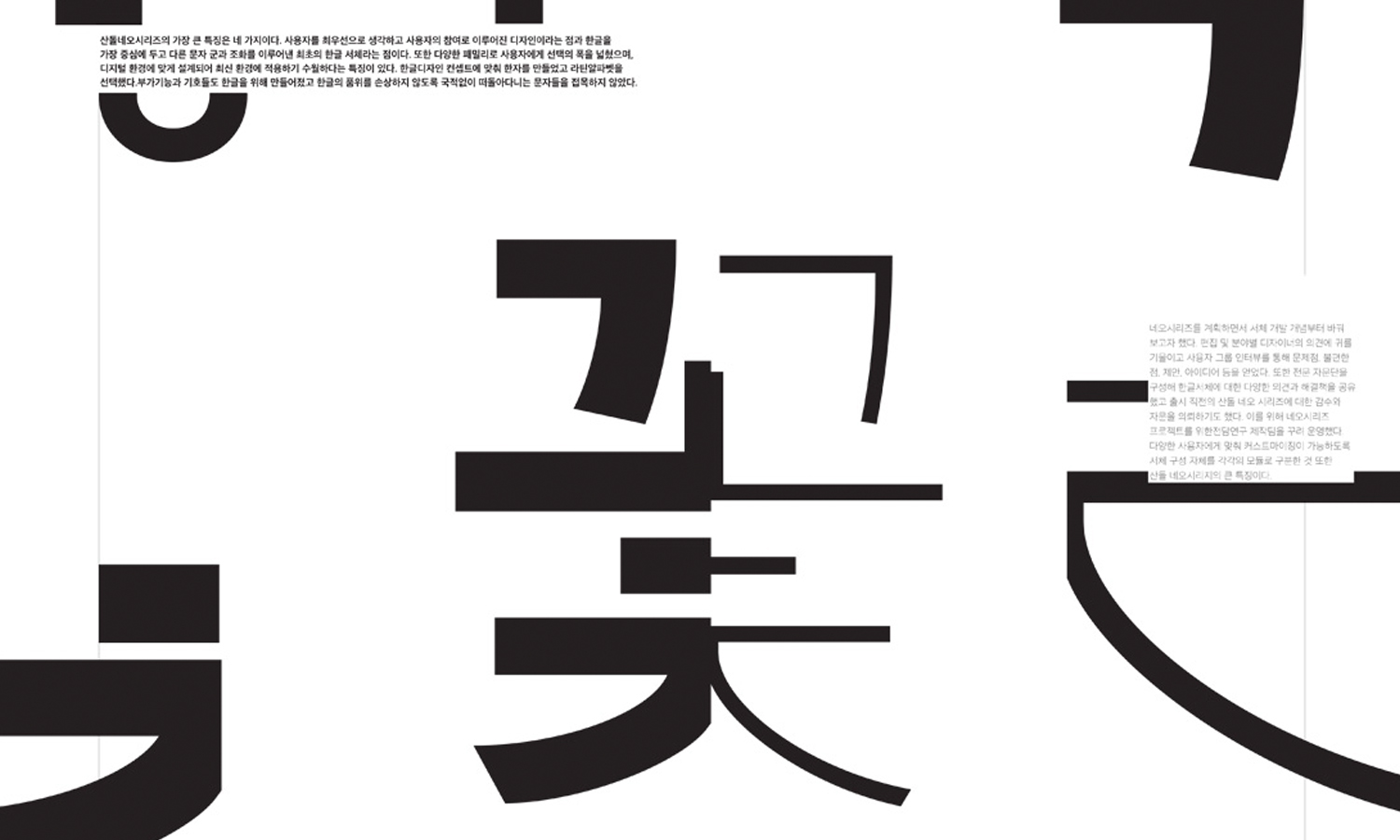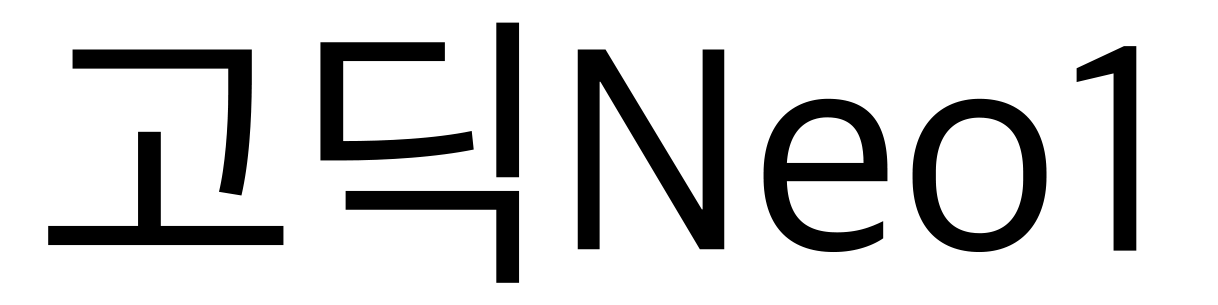
Sandoll 고딕Neo1
분류 Sans,민부리
종수 9종
산돌 고딕Neo1는 다양한 웨이트의 슈퍼 패밀리를 갖춘 프리미엄 고딕 폰트이다.
산돌의 기술과 경험을 집약한 프리미엄 본문서체 Sandoll Neo Series의 일환으로서 기존 산돌 고딕의 고전적인 모습에서 현대적인 세련됨이 돋보이도록 디자인하였다.
사용자 중심의 설계로 사용성과 가독성을 최우선으로 고려하였으며 기본적인 네모꼴에 글자와 여백을 가지런하게 안배하여 안정적인 느낌을 부여했다.
• 2011
• 권경석 이도경
• Sans,민부리
• Sandoll 고딕Neo1 / Sandoll GothicNeo1
• 제목용,UI/UX,본문용,중립적